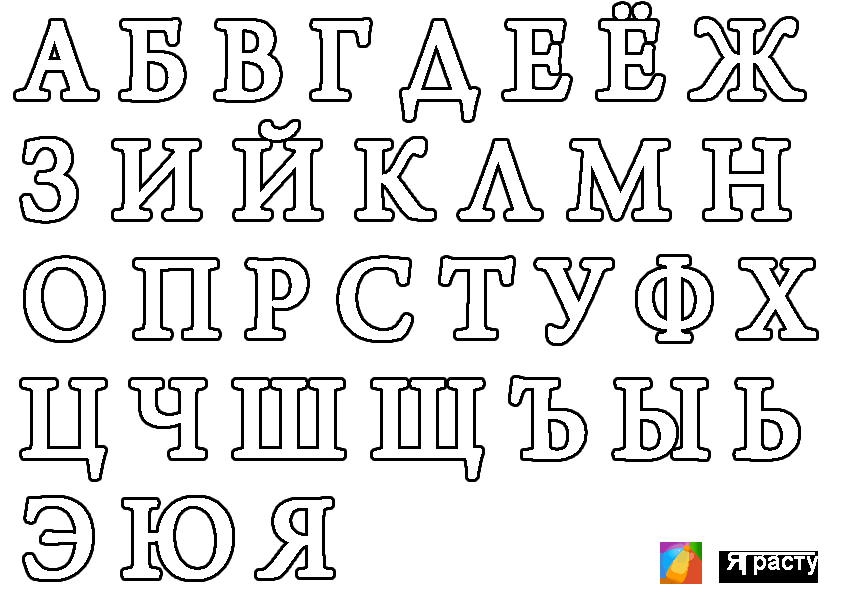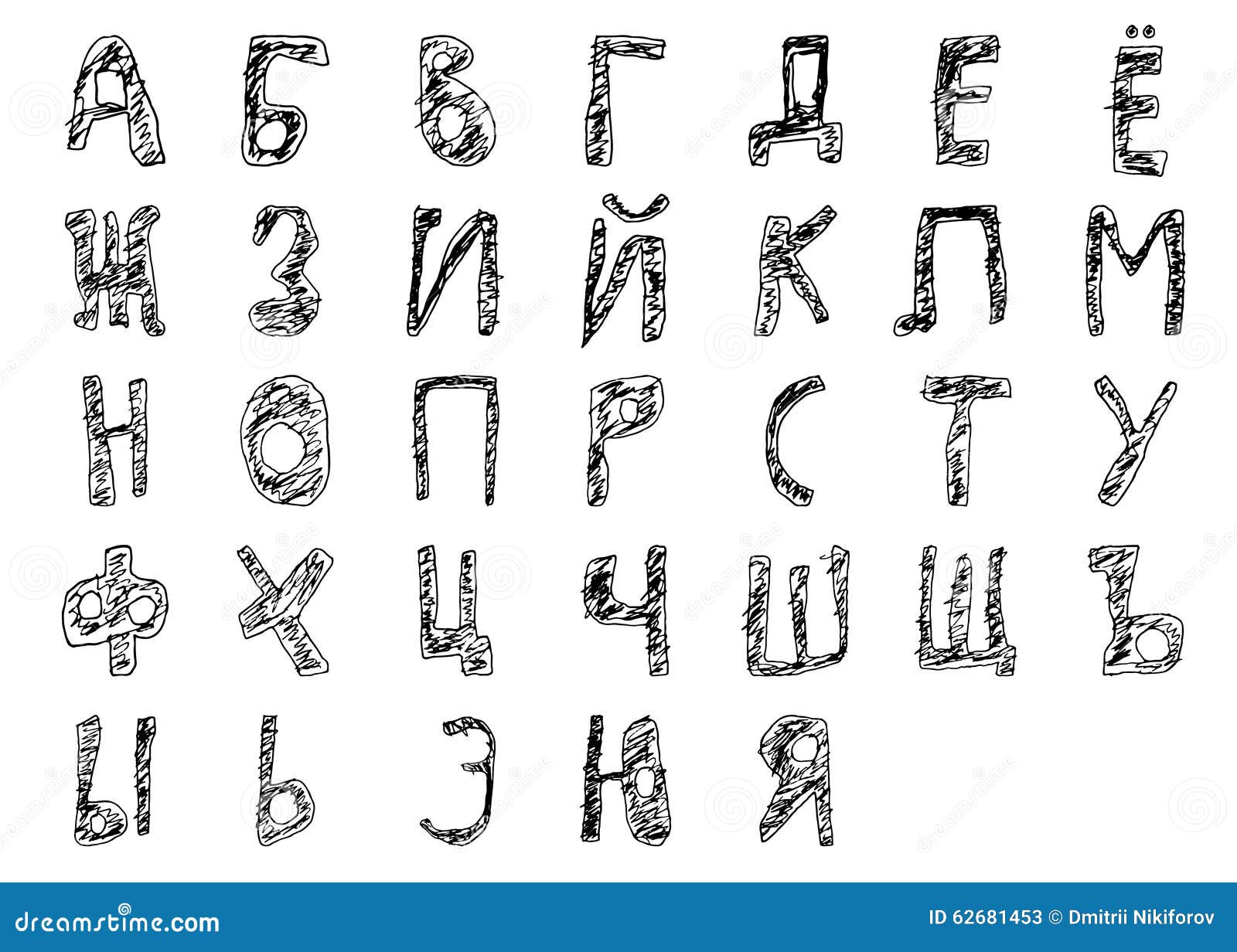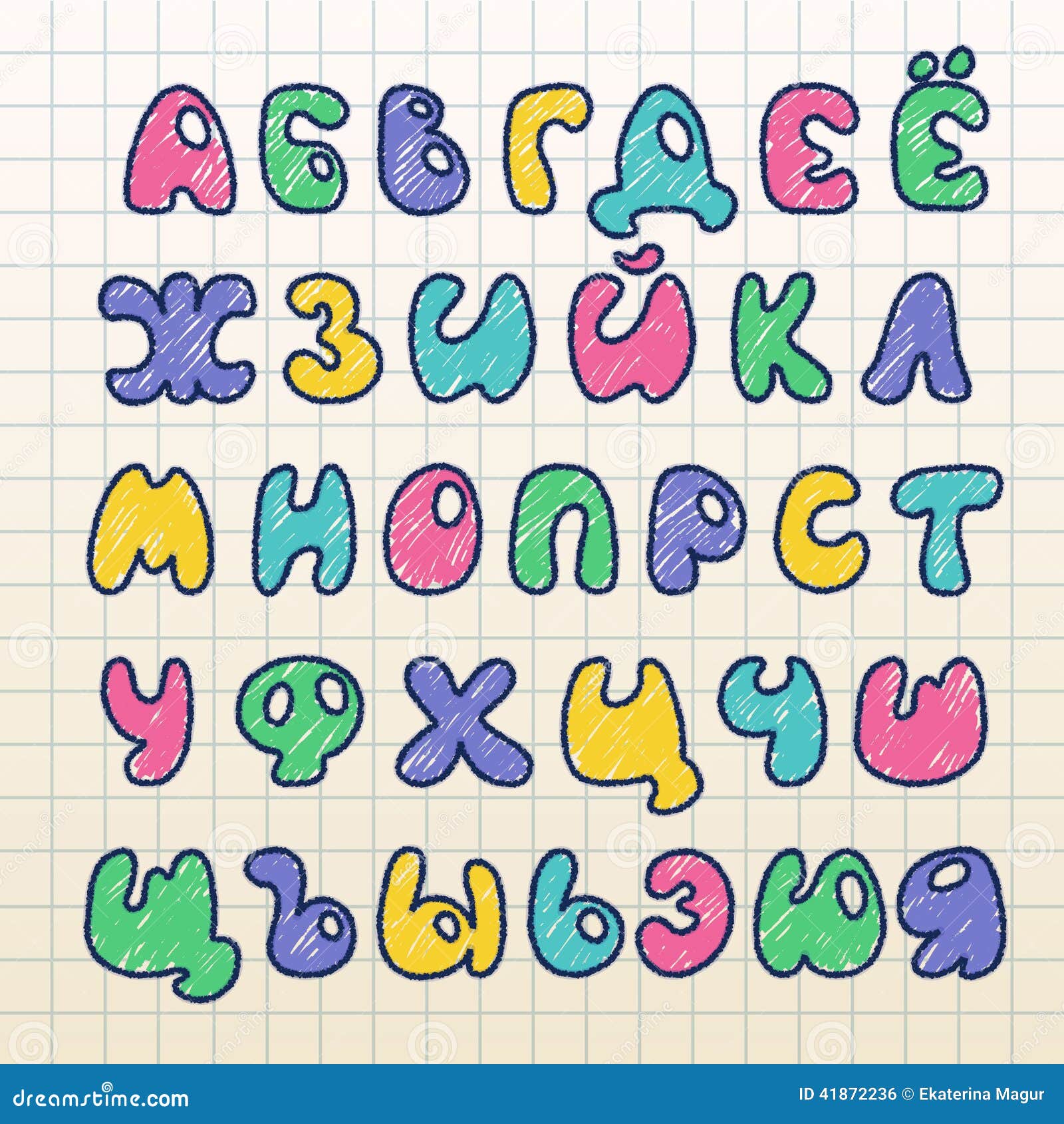
Лучшие советы по созданию красивых русских шрифтов карандашом для вашего дизайна
На этой странице вы найдете полезные советы и вдохновляющие примеры для создания рукописных шрифтов карандашом в русском стиле. Мы расскажем, как добиться четкости и выразительности, при этом сохраняя художественность и уникальность вашего письма. Подборка фотографий и рекомендаций поможет вам выбрать подходящий стиль для вашего проекта.
Для достижения четкости в русских шрифтах карандашом используйте мягкие карандаши, чтобы линии получались ровными, но не слишком темными.
Не бойтесь экспериментировать с различными типами шрифта — от строгих до более декоративных. Каждый стиль добавляет свою атмосферу.
Обратите внимание на расстояние между буквами и строками. Оставляя достаточный промежуток, вы сможете добиться лучшей читаемости.
Попробуйте создавать контуры шрифта сначала легким карандашом, а затем выделите их более темным для контраста и выразительности.
Если хотите добавить акцент на определенные слова, можно выделить их карандашным штрихом, сделав линии толще.
Для уникальности шрифта используйте различные наклоны букв и необычные соединения, чтобы придать написанному индивидуальность.
Не забывайте о пропорциях. Чтобы шрифт смотрелся гармонично, старайтесь соблюдать правильные размеры всех элементов.
Для создания текстуры используйте разные техники рисования: от плавных линий до острых углов, это добавит глубины вашему шрифту.
Если хотите добавить объема, используйте светлые и темные оттенки карандаша для создания эффектов тени и света.
Помните, что самое важное в рукописном шрифте — это ваша уникальная идея. Не бойтесь добавлять элементы, которые подчеркнут ваш стиль и индивидуальность.